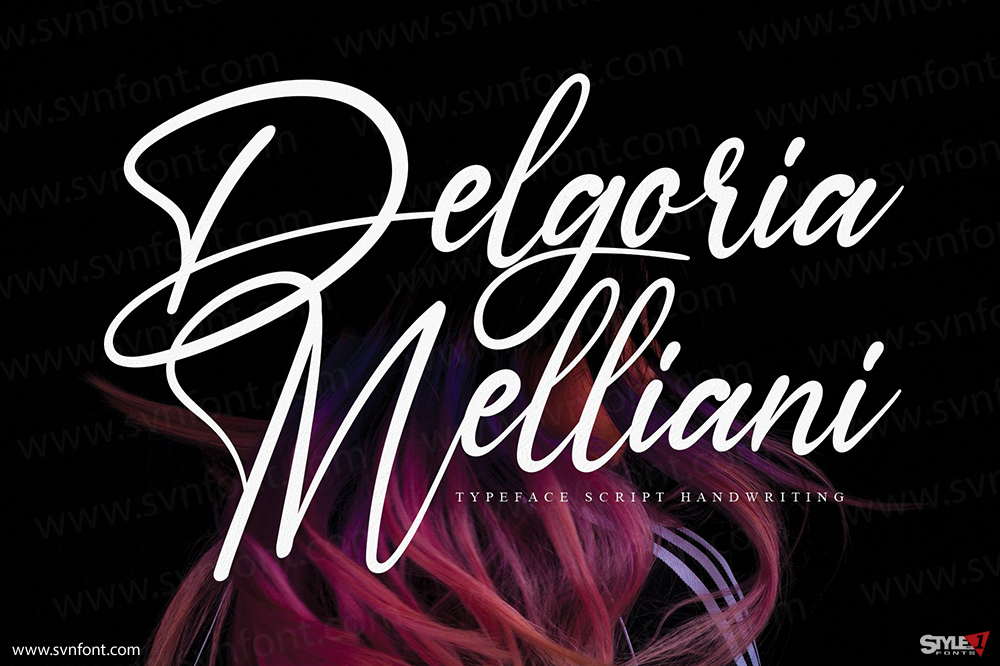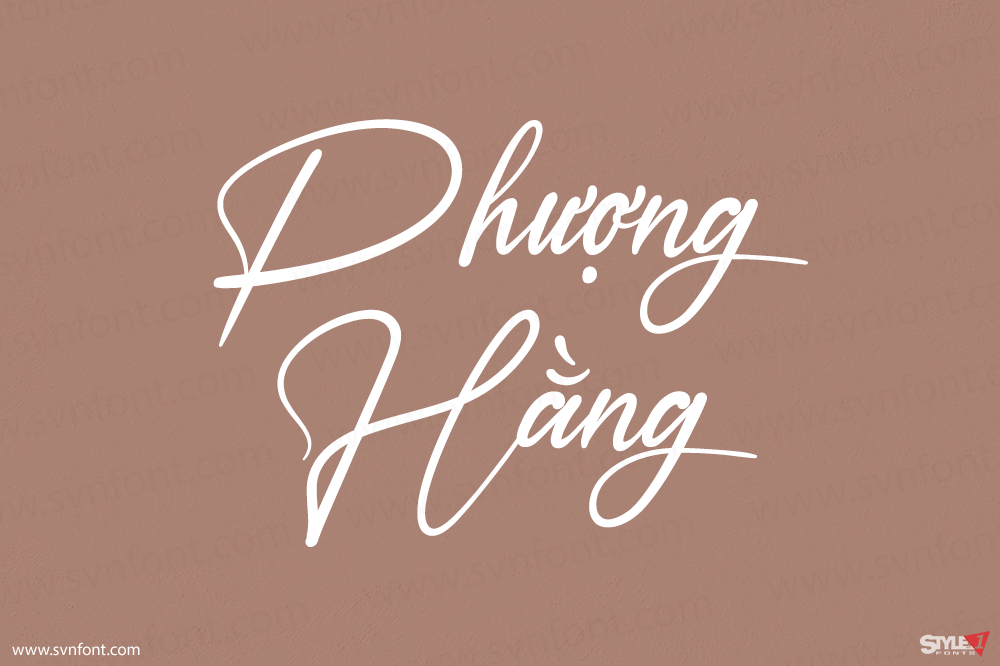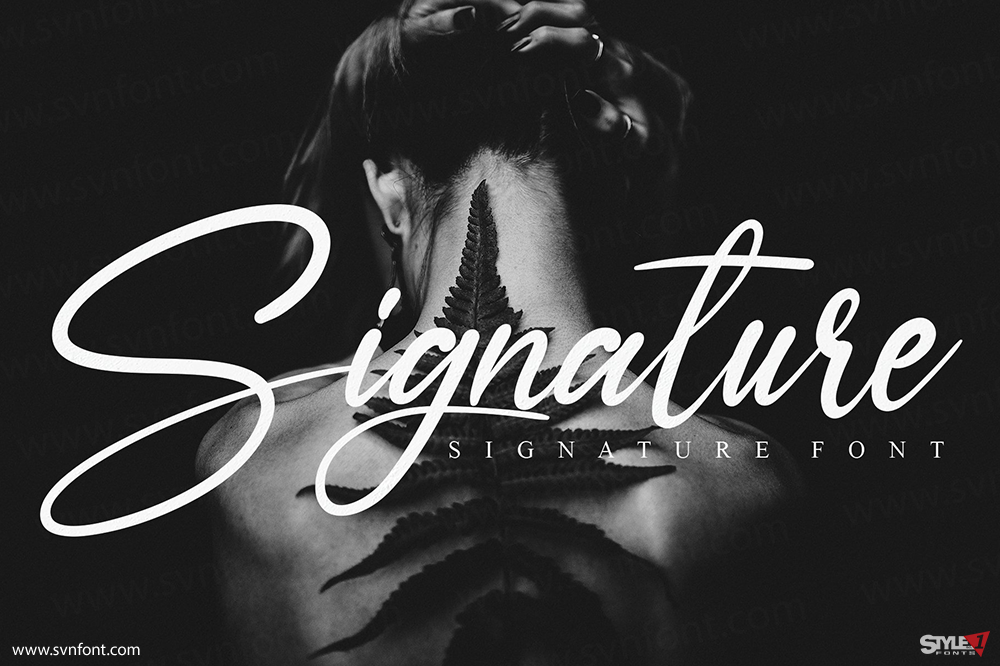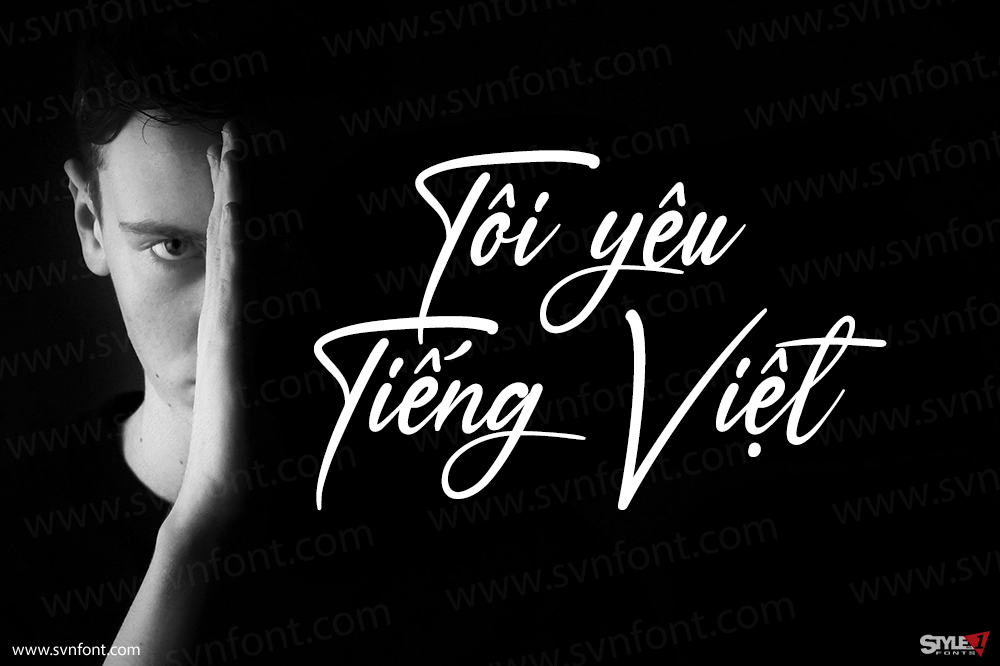
Ameyallinda Signature – kiểu chữ phong cách mới nhất hoàn hảo cho trang trí tường, thiệp mời đám cưới, logo bài đăng trên mạng xã hội, quảng cáo, bao bì sản phẩm, thiết kế sản phẩm, nhãn mác, nhiếp ảnh, hình mờ, thiệp mời, văn phòng phẩm và bất kỳ dự án nào đòi hỏi nét chữ viết tay tinh tế.
Nhà thiết kế: scratchones
Nhà phát hành: scratchones